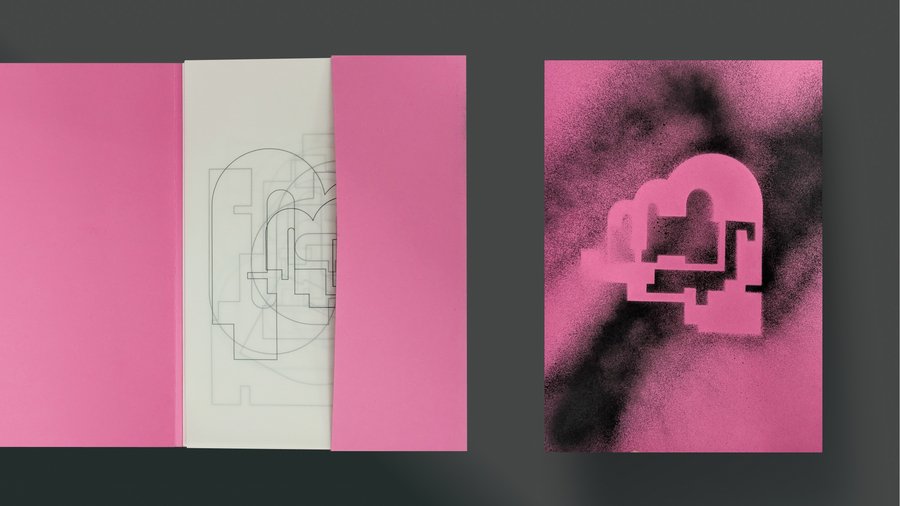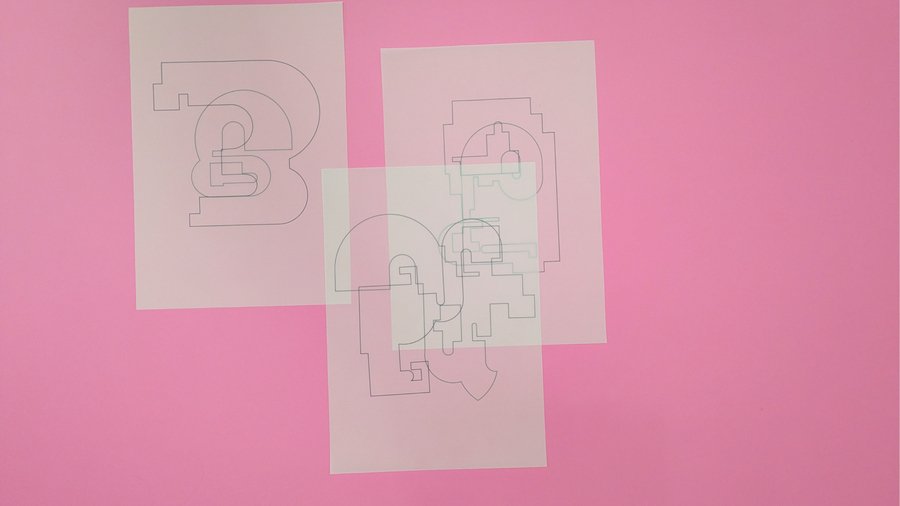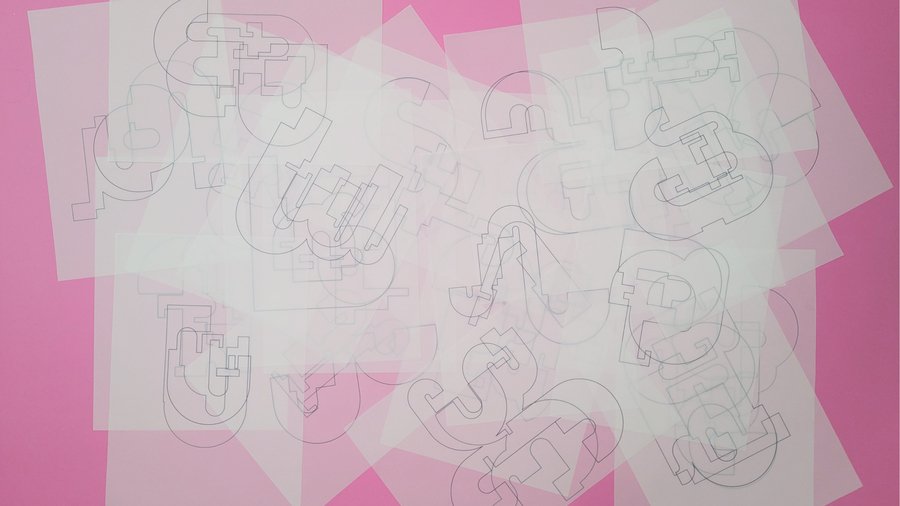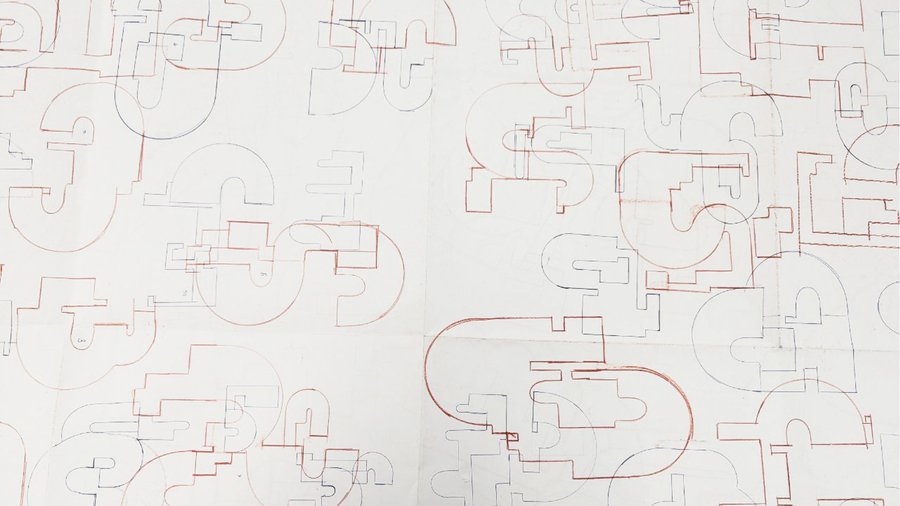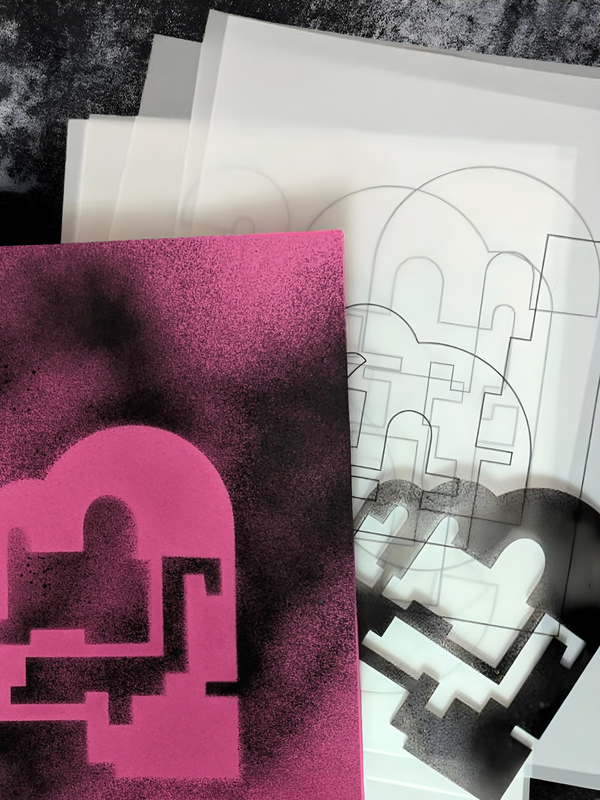
Проект-наблюдение за городской средой и собственными ощущениями.
Модульный шрифт вдохновлённый рисунком фундамента. В этом проекте я нашла образ на пересечении картографии и собственных ощущений от граней и линий среды